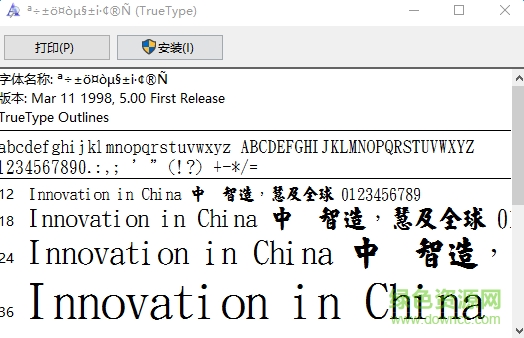
金梅毛筆張楷書字體是一款很實(shí)用的電腦字體,也是一款很不錯(cuò)的毛筆字體,寫出來的字粗厚穩(wěn)重,給人一種很踏實(shí)的感覺,不知道大家是否喜歡這款字體呢,喜歡就來綠色資源網(wǎng)下載吧。
金梅毛筆張楷書字體就是一種很不錯(cuò)的毛筆字體,用于毛筆練字或者是寫作還是可以的,歡迎大家來綠色資源網(wǎng)下載使用。